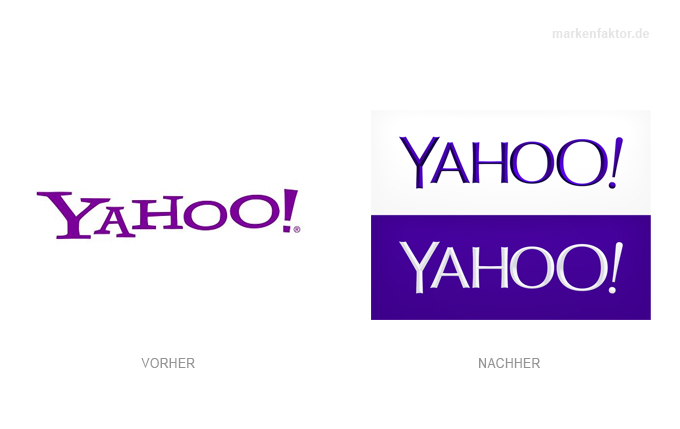
Yahoo mit neuem Logo
Es ist offensichtlich ein Trend, sich von frei gestalteten Logos zu verabschieden, und stattdessen einfache schlichte Wortmarken mit irgend einem fertigen Font zu schreiben.
Auch das Internet-Versteigerungshaus eBay hatte vor noch gar nicht so langer Zeit ein Logo aus ähnlich tanzenden Buchstaben, wie das alte Yahoo Logo. Auch dort wurde das über viele Jahre bekannte eBay-Logo durch ein schlichtes ebay aus einfachen Buchstaben ersetzt, lediglich die Farben sind geblieben, aber auch darauf kann man ja noch verzichten.
Und jetzt hat Yahoo eben nachgezogen und ist praktisch den gleichen Weg gegangen: weg von den frei gestalteten und wild umher tanzenden Buchstaben, hin zu einem einfachen geraden Text. Wer weiß, beim nächsten Logo verschwindet dann vielleicht auch noch das größere Y und man lässt vielleicht sogar auch noch das ! weg.